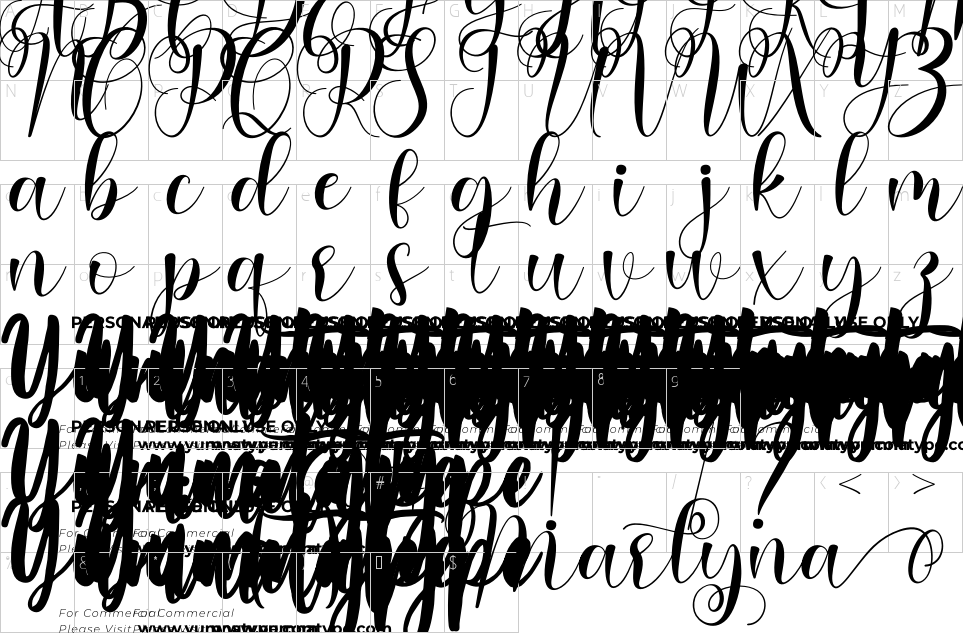
A fonte Marlyna, disponível gratuitamente para download, é um recurso visual agradável para designers e profissionais de gráfica. Desenhada pela equipe da Yumna Type, esta fonte é perfeita para aqueles que procuram um estilo alegre e atraente. Com um design fluido e harmonioso, Marlyna é uma escolha inteligente para aplicar em textos de e-mail, posts de redes sociais ou até mesmo em pequenos detalhes de design. Com sua simplicidade, a fonte oferece um toque amigável que combina bem com uma variedade de projetos. Seja para uso pessoal ou comercial, Marlyna é uma ótima opção para aqueles que procuram uma fonte gráfica atraente e versátil. Em uma categoria repleta de fontes gratuitas, Marlyna não apenas se destaca por seu design agradável, mas também pela sua grande aceitação, já que foi baixada mais de 1.417 vezes.